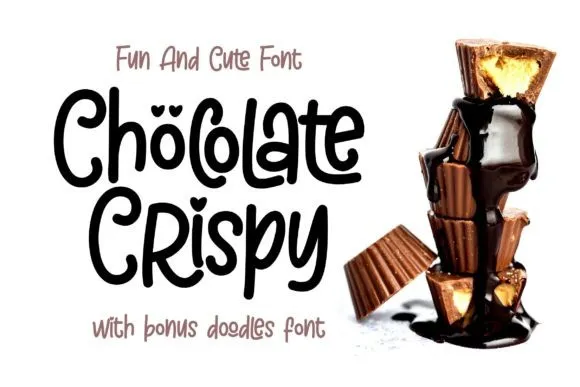
Chöcolate Crispy – Fun and Cute Font – Fonte Grátis
Chöcolate Crispy - Fun and Cute Font
A fonte ‘Chöcolate Crispy – Fun and Cute Font’ é uma opção perfeita para aqueles que buscam algo divertido e alegre para suas próximas criações gráficas. Escrevendo à mão, essa font oferece um toque fresco e adoravelmente curioso, capaz de transformar qualquer ideia em uma peça realmente destaca-se. A ergibi studio é o criador desta font divertida e alegre que você pode incorporar em vários projetos futuros. Ela foi especialmente concebida para dar um toque elegante e alegórico aos seus trabalhos. Perfeito para aplicação em diversas áreas, desde projetos de arte digital até projetos do lar, Chöcolate Crispy será seu amigo perfeito para qualquer ideia que envolva muitas palavras. Utilize-a em projetos de decoração de casa, convites para festas e até mesmo para rótulos de sinais. É uma escolha sólida para aqueles que procuram um toque alegre em seus trabalhos sem comprometer a qualidade ou a legibilidade da fonte.